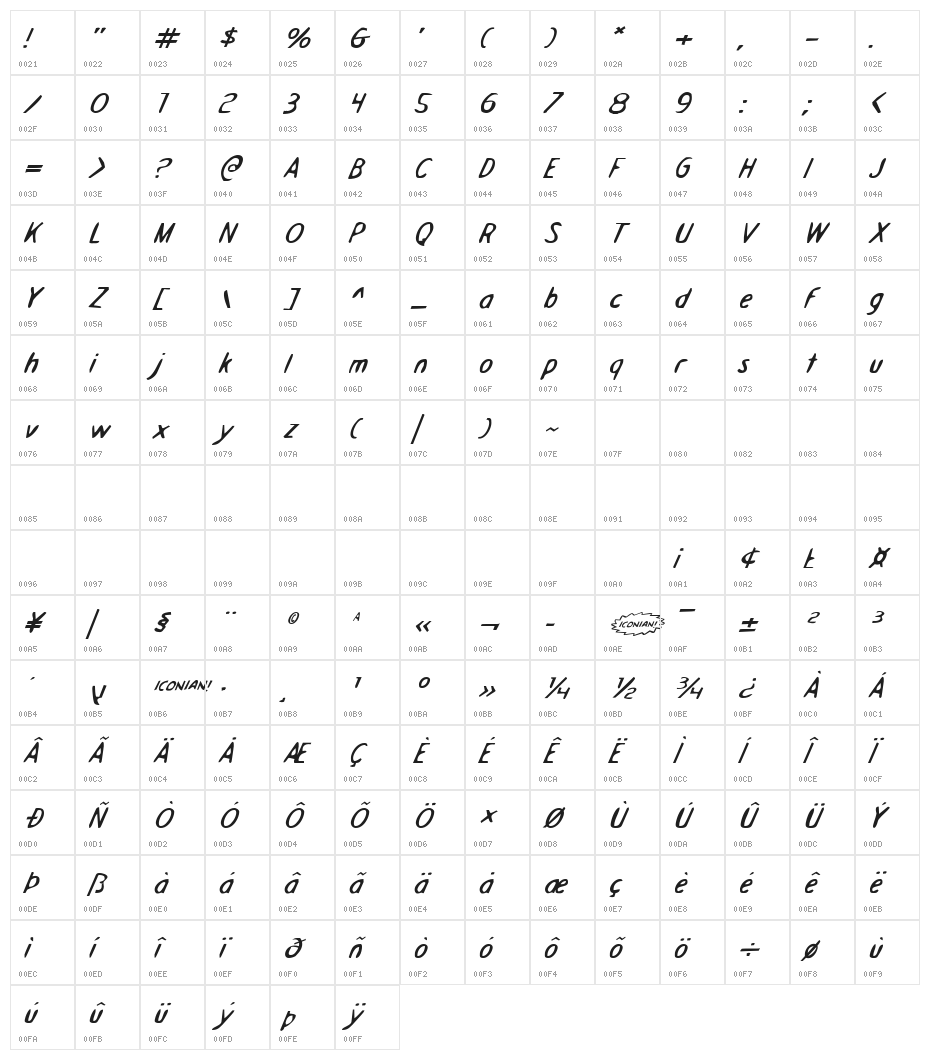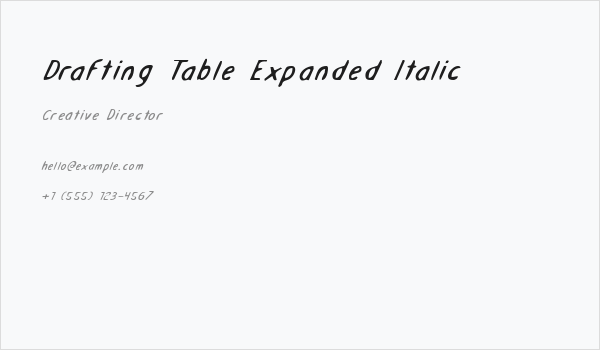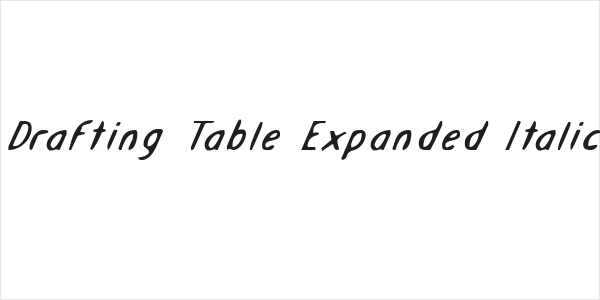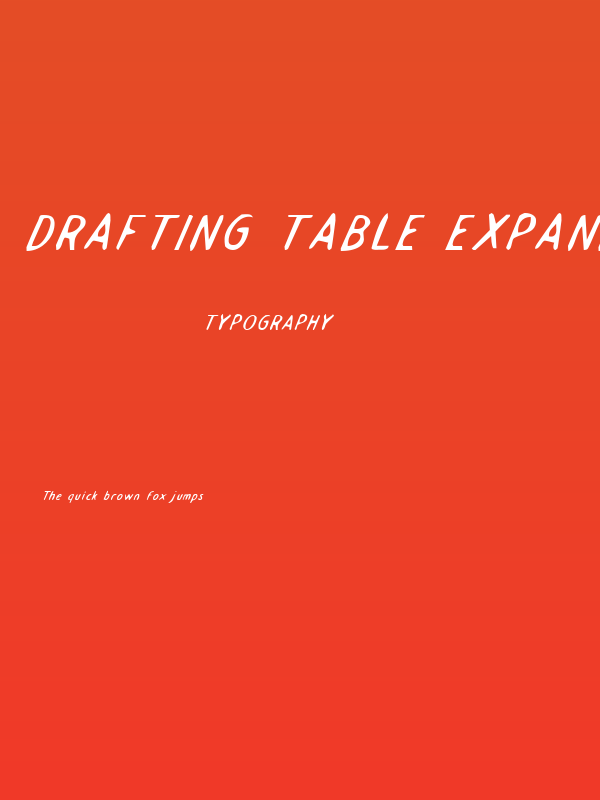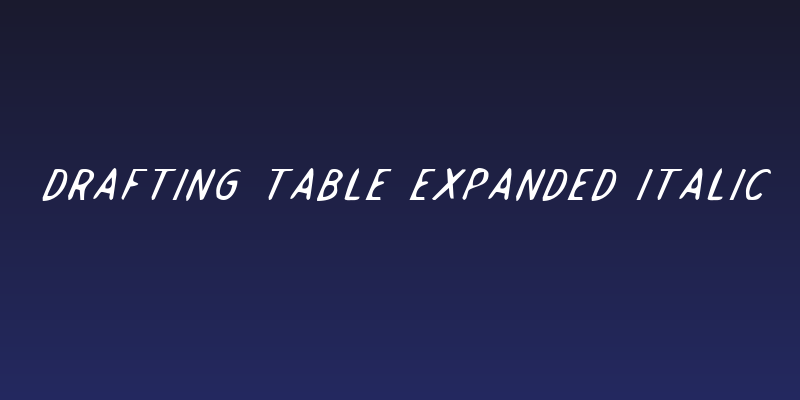
Drafting Table Expanded Italic Font
| Caso d'uso | Logos, Headlines, Branding |
| Progetti proposti | Ideal for branding, advertising, and editorial design where a modern and elegant look is desired. |